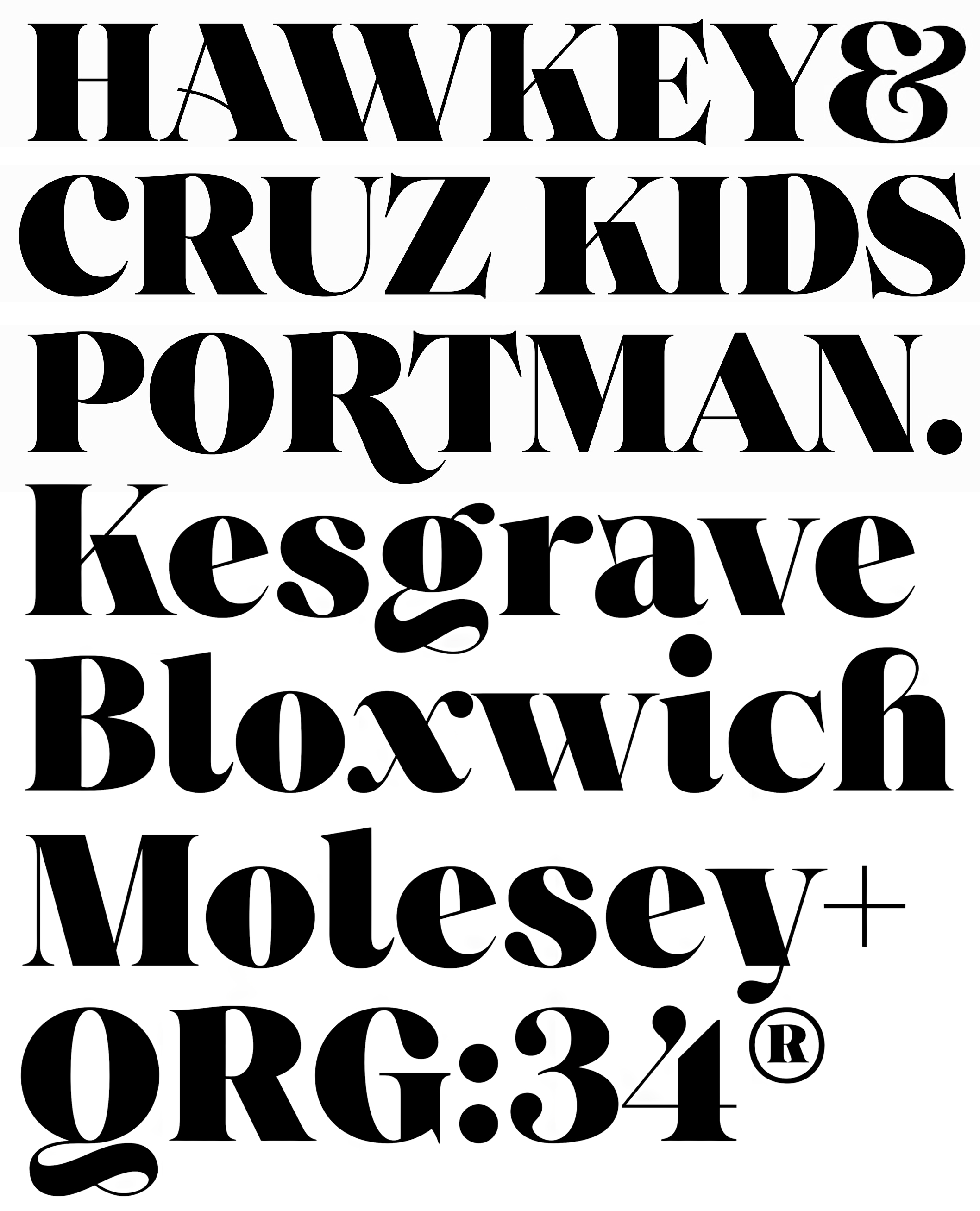
| Descripción | Princesa representa un fascinante viaje a través del tiempo, inspirándose en las fuentes romanas clásicas y abordando con maestría los retos tipográficos contemporáneos. |